오징어 게임의 인기에 힘입어 폰트에 대한 관심도 많아지고 있다. 오징어 게임 폰트 다운로드 하는 방법과 저작권, 세모 네모 동그라미를 적용하여 활용하는 방법을 소개한다.
오징어 게임 폰트 다운로드 저작권 활용 폰트 세모 네모 동그라미 적용 방법
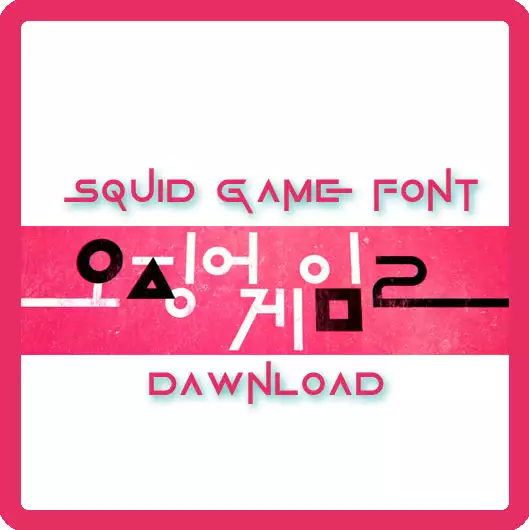
오징어 게임 폰트 다운로드 (영문)
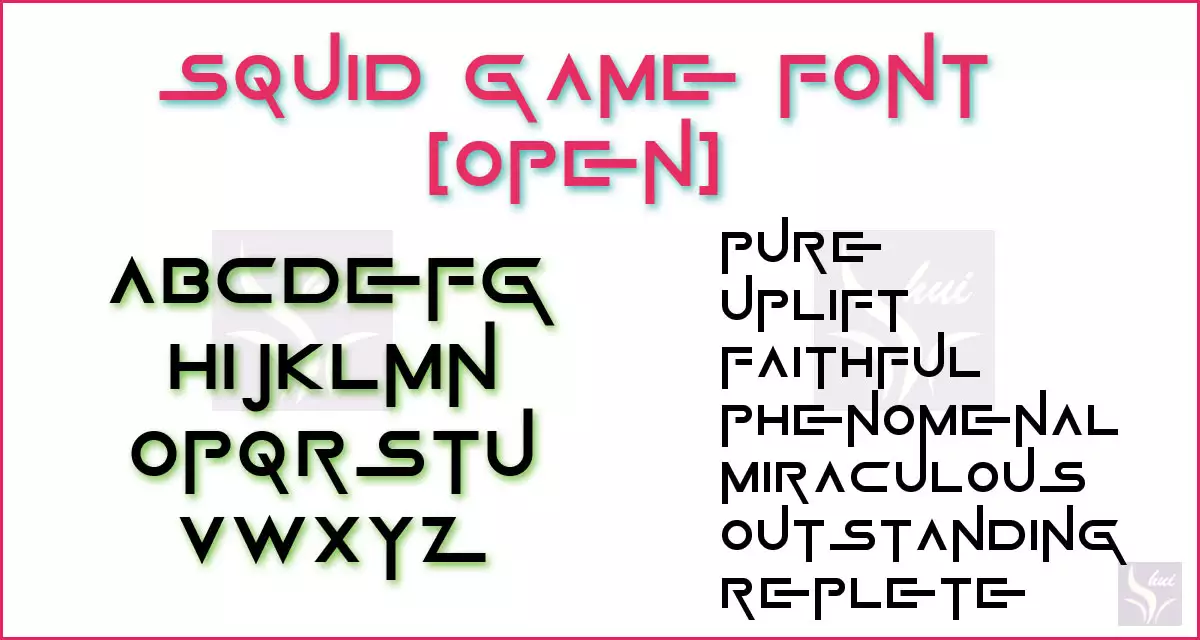
처음 찾았던 폰트는 squid game폰트이다. Darrell Flood Fontographer가 오징어 게임1 드라마가 세계적으로 인기를 얻은 이후 개발한 폰트로 무료로 사용가능하다. 영문 대문자만 가능하여 영문 작업 시 적절히 활용하면 좋을 듯하다.
사무적으로 딱딱한 듯하지만 팬시적 요소가 가미되어 있고, 쭉쭉 늘어난 글자의 끝맺음이 왠지 오징어 긴다리를 연상시킨다. 몇 자 적어보았는데 타이틀용으로 적절히 사용하는 것이 좋겠다. 본문용이나 긴 나열식 제목에 사용하니 가독성이 떨어지는 듯하다.
오징어 게임 폰트 Rix 오징어 (한글)
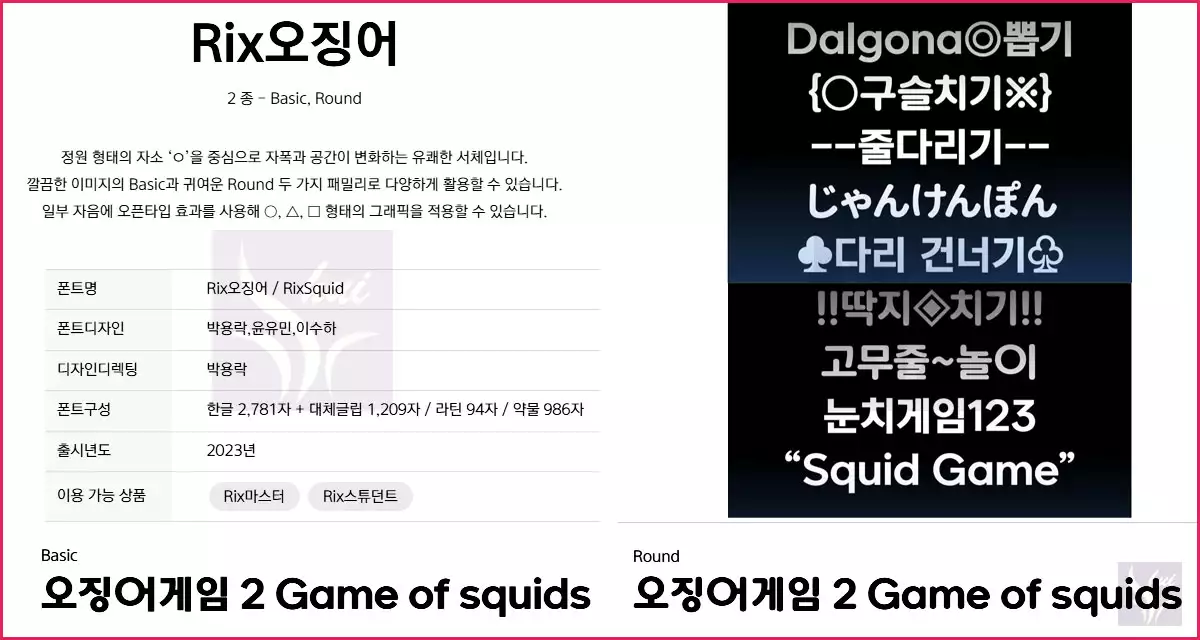
다음은 오징어 게임 폰트로 활용이 가능한 Rix 오징어 폰트이다. 어릴 적 수채화 포스터 작업시 자주 사용했던 글씨체와 모양이 비슷하다. 귀여운 폰트. Rix 폰트에는 다양한 형태의 폰트가 많이 있다.
그중 Rix오징어 폰트는 한글 2,781자와 대체글립 1,209자, 라틴 94자, 약물 986자로 구성되었으며 2023년 출시되었다. 영문 일어 외 기호 등 자유자재로 구현된다는 것이 위 영문 폰트보다는 활용도가 월등히 높을 듯하다.
오징어 게임 폰트 Rix 오징어 대체글립 적용
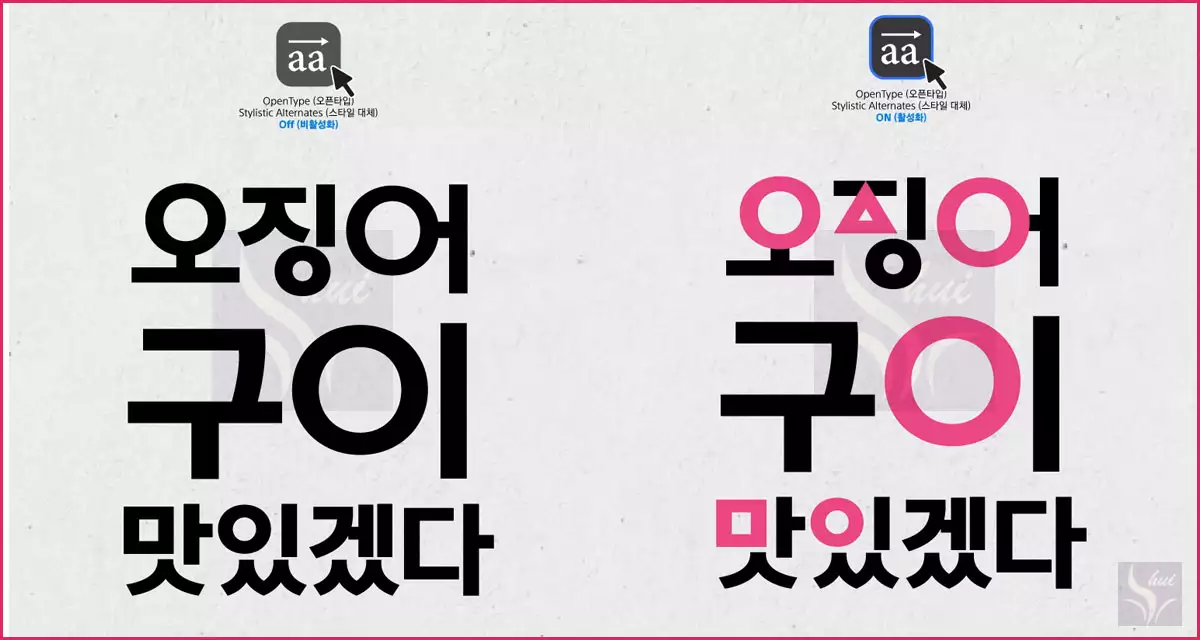
Rix오징어 폰트는 포토샵 CC 이상 버전에서 대체 글립을 적용해 오른쪽과 같이 오징어 게임의 타이틀처럼 변형이 가능하다.